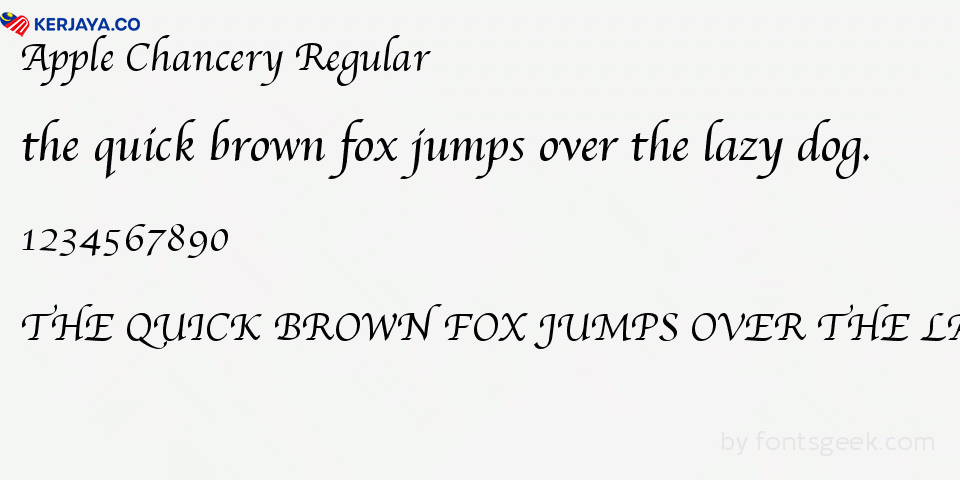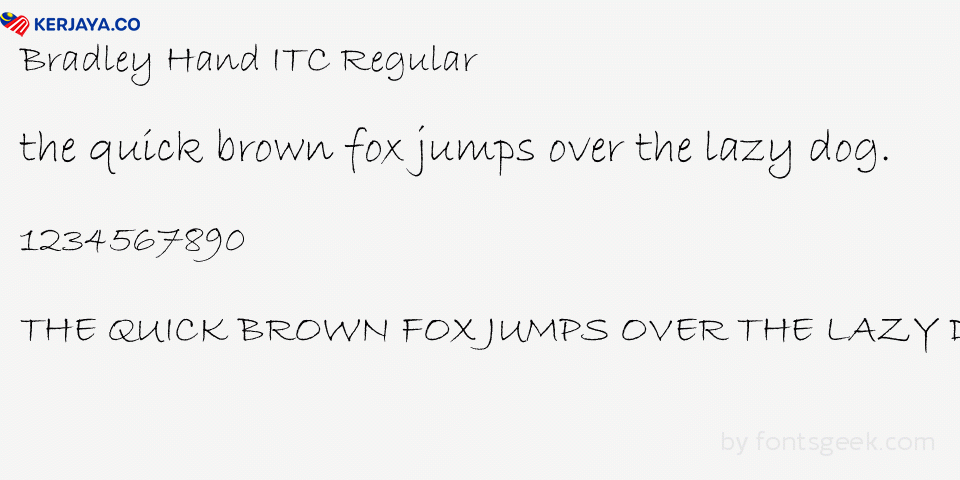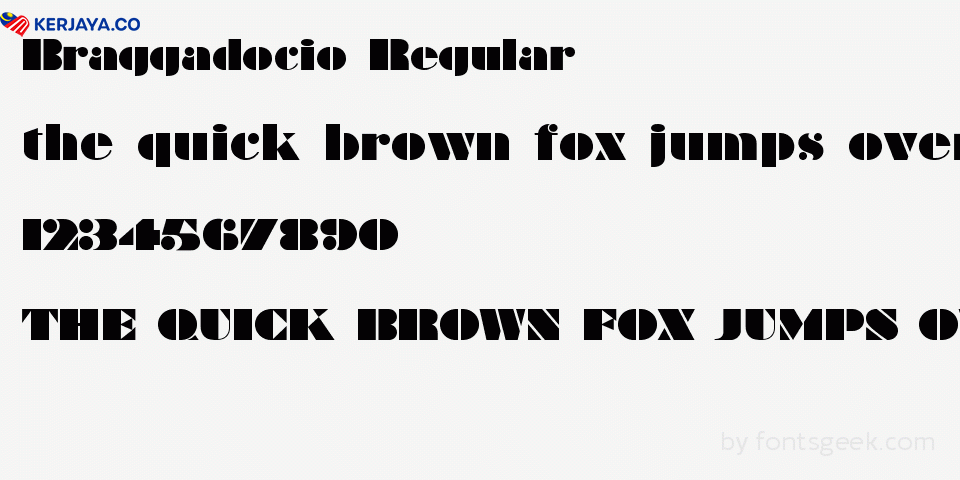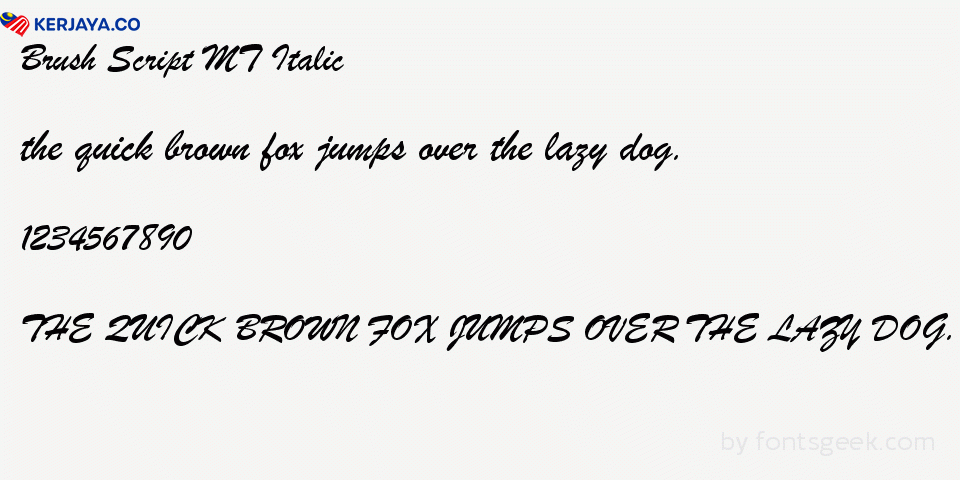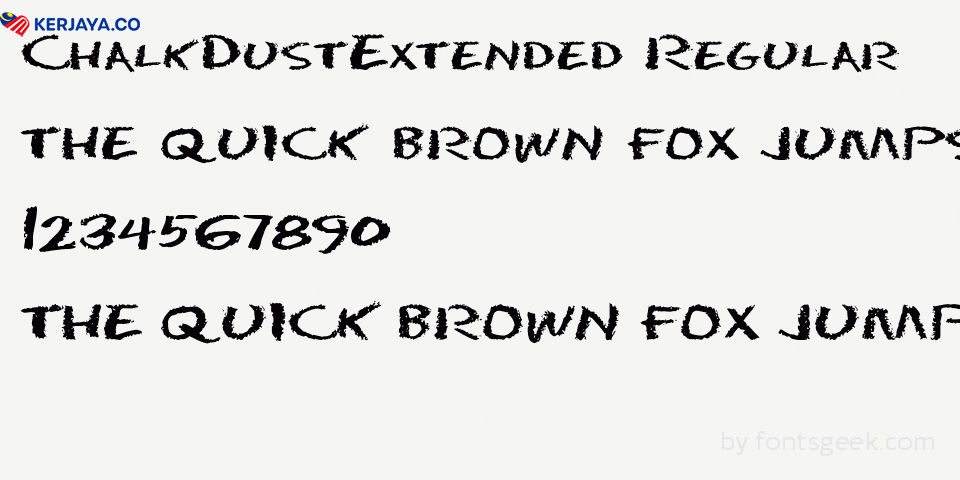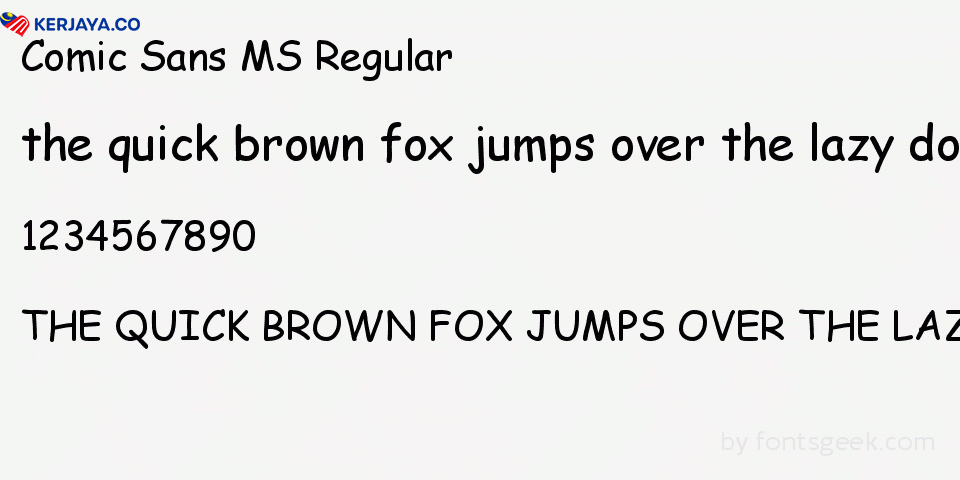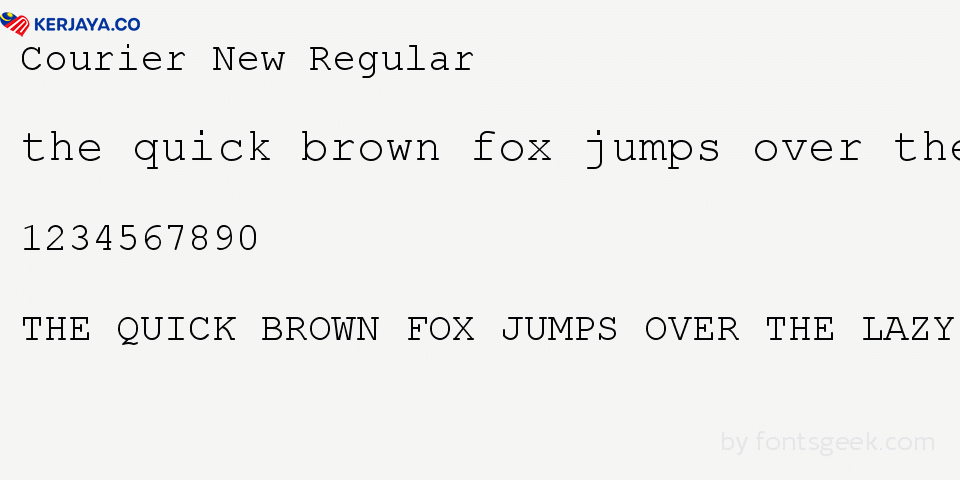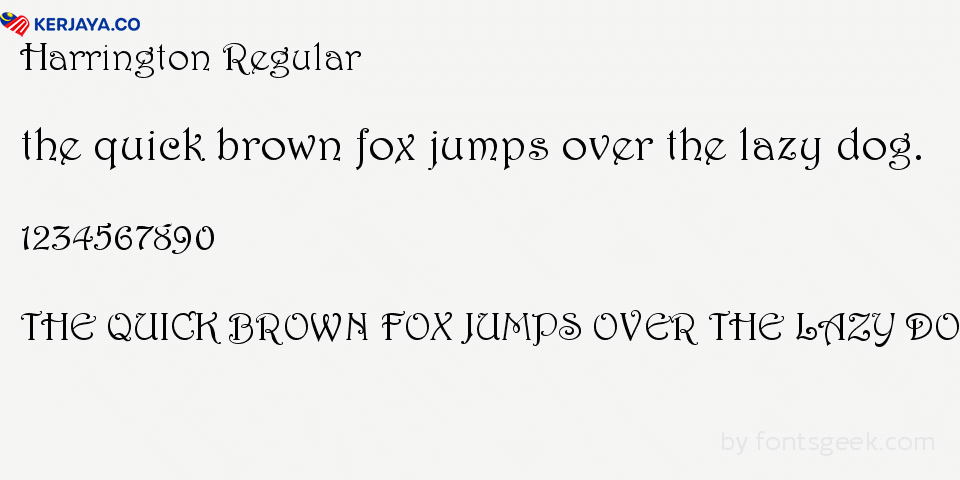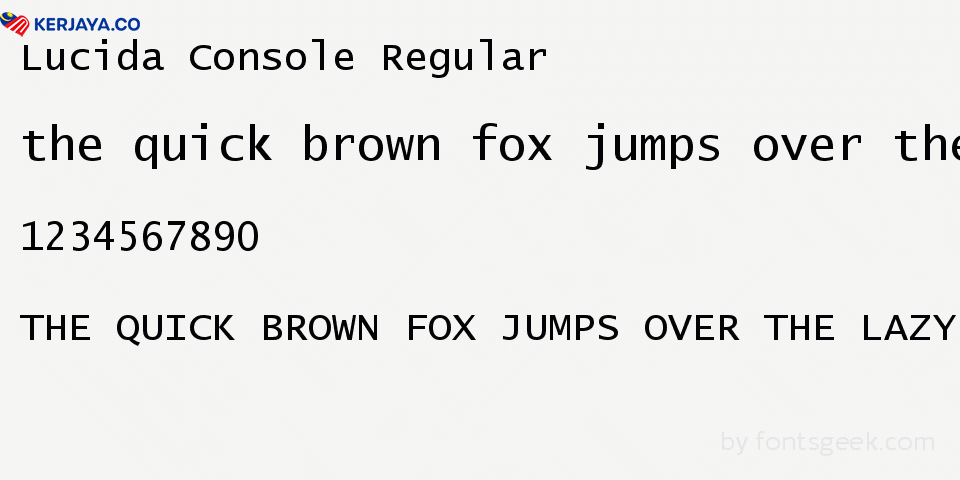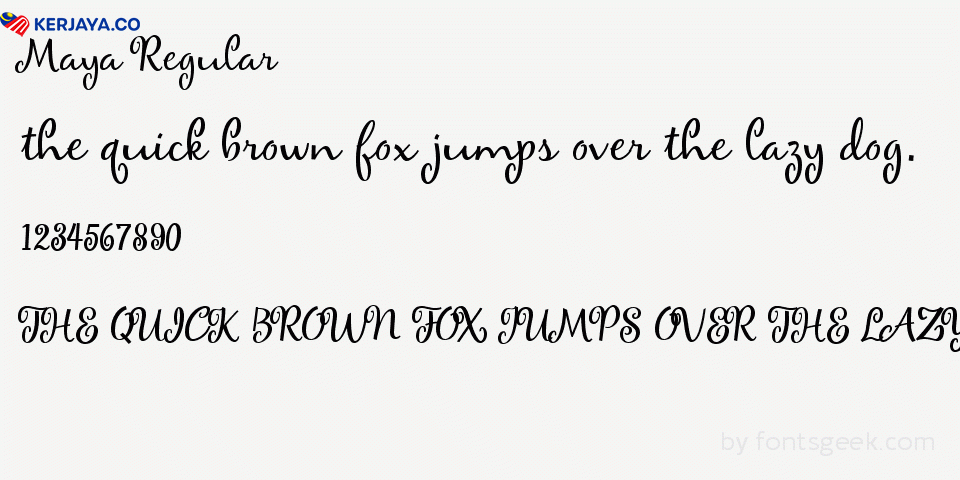
10 Jenis Font Tulisan Yang Anda Tidak Boleh Guna Untuk Menulis Resume
Memang tidak dapat dinafikan bahawa graduan pada hari ini sememangnya kreatif dan kaya dengan idea yang menarik. Jadi, tidak hairanlah jika resume yang disediakan oleh graduan pada hari ini sangat cantik dihiasi dengan hiasan-hiasan grafik.
Resume yang cantik ini memanglah ada kelebihannya iaitu untuk menarik perhatian penemuduga tetapi anda harus tahu bahawa hiasan mestilah tidak terlalu fancy sehingga menjadikan resume tersebut tidak lagi formal dan mengganggu penemuduga untuk membacanya.
Salah satu aspek yang perlu anda ambil berat dalam penghasilan resume adalah font atau jenis tulisan. Dalam artikel ini, kami akan kongsikan 10 jenis font yang anda dilarang sama sekali untuk gunakan dalam membuat resume.
Berikut merupakan 10 jenis font tulisan yang anda tidak boleh guna untuk menulis resume.
COURIER NEW
Font jenis ini selalunya digunakan oleh pelajar-pelajar sekolah dalam membuat karangan. Tulisannya sangat besar serta jelas dan juga akan memakan ruang yang sangat banyak. Jadi, hanya sedikit maklumat dapat dimuatkan dalam satu mukasurat. Oleh sebab itulah, anda tidak boleh menggunakan font ini untuk menulis resume.
LUCINDA CONSOLE
Font ini pula kelihatan seperti boleh diterima tetapi sangat memakan ruang yang besar dan banyak. Jadi, bukan sahaja banyak mukasurat diperlukan malah penemuduga juga sukar untuk mendapatkan mesej yang ingin anda sampaikan.
COMIC SANS
Jika anda perhatikan betul-betul pada jenis font ini, anda akan dapati font Comic Sans sebenarnya adalah berbentuk kasual dan tidak sesuai sama sekali untuk digunakan bagi tujuan formal.
Tulisan bagi font jenis ini berbentuk senget dan bentuknya kelihatan seperti bulat-bulat. Jadi, font ini sangatlah tidak sesuai. Ingat! Ini adalah resume dan bukannya komik santai.
BRADLEY HAND ITC
Font Bradley Hand ITC pula sebenarnya merupakan satu jenis font yang sesuai digunakan untuk tujuan board games. Hanya gamers yang ramai menggunakan font ini. Jika anda perasan, bentuk tulisannya juga seperti tulisan permainan scrabble.
BRUSH SCRIPT
Font jenis Brush Script adalah untuk tujuan penulisan skrip seperti skrip drama dan sebagainya. Anda sekarang sedang menulis resume dan bukannya proposal skrip. Jadi, hindarilah daripada menggunakan font jenis ini.
CHALKDUSTER
Walaupun zaman telah berkembang moden dengan perkembangan ICT yang pesat namun, konsep tulisan kapur pada papan hitam masih lagi diiktiraf melalui font ini. Jadi, font Chalkduster tidaklah sesuai untuk penulisan resume.
APPLE CHANCERY
Sungguhpun font ini cantik kerana bentuknya kelihatan seperti tulisan berangkai ataupun “cursive writing” namun anda dilarang sama sekali untuk gunakannya untuk menulis resume. Mengapa?
Anda mungkin menyangka font yang cantik akan menarik minat penemuduga. Salah sama sekali. Penemuduga hanya mahu melihat font yang formal dan selaras. Font yang cantik ini sama sekali tidak dilihat oleh penemuduga sekaligus beliau turut akan melabel anda sebagai tidak tahu tulisan formal.
MAYALAM MN
Font jenis ini mempunyai tulisan yang berbentuk terlalu narrow dan sebenarnya sangat sukar untuk dibaca. Walaupun bentuknya itu stylish dan sesuai dengan gaya moden sekarang, namun anda harus ingat dalam penghasilan resume, itu tidak penting. Jadi, jangan gunakan font ini.
HARRINGTON
Sekali pandang pun anda sudah tahu bahawa font jenis Harrington tidak sesuai untuk penulisan resume. Bentuknya yang comel ini lebih sesuai digunakan dalam penghasilan tulisan buku cerita kanak-kanak sahaja tetapi tidak untuk penghasilan resume.
BRAGGADOCIO
Font ini kelihatan unik dan sangat sesuai digunakan dalam penghasilan poster. Tulisannya yang besar dan jelas itu memudahkan orang lain untuk membacanya. Namun, dalam menulis resume, janganlah gunakan font ini. Bayangkan dengan tulisan sebesar itu, berapa mukasurat yang anda perlukan untuk resume anda. Oleh sebab itulah font ini tidak sesuai digunakan.
Meskipun kelihatan remeh, namun pemilihan font adalah sangat penting dalam membuat resume. Jangan sesekali menggunakan kesemua 10 font yang disenaraikan di atas. Gunakanlah font yang selaras. Contoh font yang selaras adalah seperti Times New Roman dan juga Arial. Selamat menulis resume!